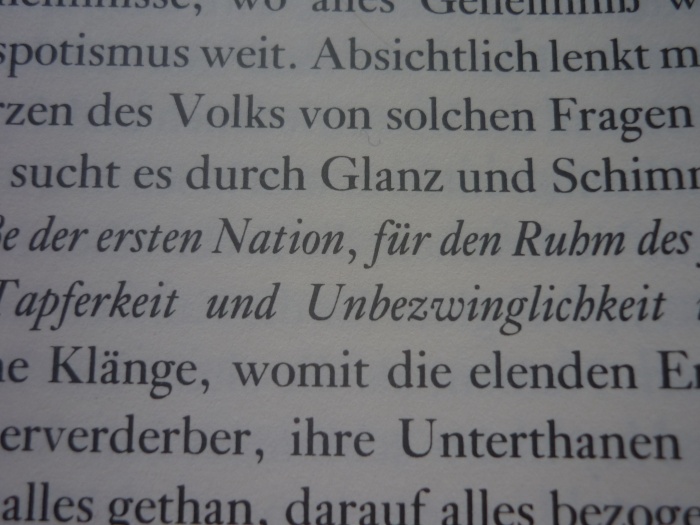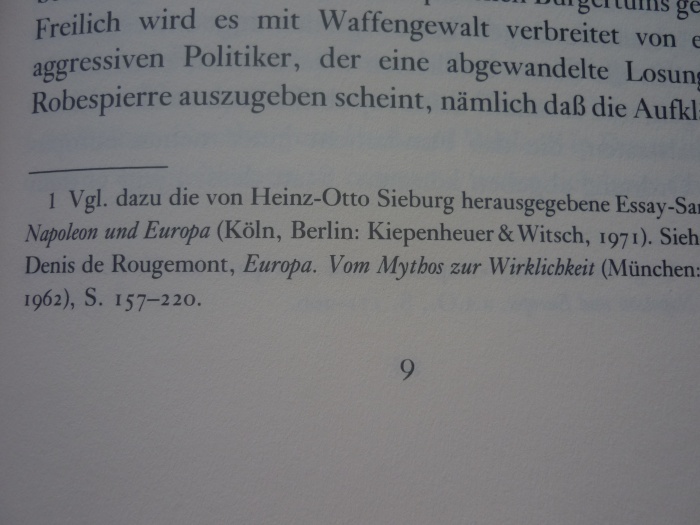
Schriftart insel-Taschenbuch
ich bin zur Zeit auf der Suche nach einer speziellen Schriftart, die im (alten) insel-Taschenbuch Nr. 638 verwendet wurde. Es scheint eine Baskerville zu sein. Folgende Baskerville-Varianten habe ich bereits ausgeschlossen:
ITC New Baskerville Pro
Baskerville Handcut OT
Baskerville FS
Zum Buch selbst können folgende Angaben gemacht werden:
Titel: Europa. Analysen und Visionen der Romantiker.
Hrsg: Paul Michael Lützeler
Satz: Fotosatz Otto Gutfreund, Darmstadt
Verlag: INSEL
Jahr: 1982
Ich habe zwei Bilder zur Identifizierung angehangen. Ich hoffe es findet sich jemand, der bei diesem Fall behilflich sein kann.
PS: Das kursive „J“ hat keinen horizontalen Strich.
Gelöst von Albert-Jan Pool
Eine Baskerville kann es nicht sein, es ist die Linotype Janson. Schau beispielsweise mal genauer auf a und g. Viel zu asymmetrisch um für eine Baskerville durchgehen zu können. Bei Antiqua-Schriften bringt oft einen Vergleich der Kursiven die entscheidende Hinweise.
Die Linotype Janson gibt es bei Linotype nicht mehr. Die Janson wurde in von Stempel für Linotype überarbeitet und ausgebaut als Janson Text, die Schriftfamilie erschien 1986. Dabei wurde anscheinend der Querstrich im J in allen Schnitten wieder eingeführt.
Die Digitalisierungen von Bitstream basieren auf die der Linotype Bibliothek, praktisch so wie sie 1980 bei der Gründung der Firma Bitstream von den ehemaligen Linotype-Mitarbeitern ‘übernommen’ wurde. Aber Bitstream und Linotype gehören inzwischen beide Monotype und auf linotype.com findest Du also jetzt die Linotype Janson die da aber Kis heißt. Die heißt so, weil man später entdeckt hat, dass die Janson eigentlich nicht von Janson ist, aber von Nicolas Kis geschnitten wurde.
Die URW Janson entspricht anscheinend ebenfalls die Linotype Janson, aber so wie es aussieht wurde sie ergänzt um die (wahrscheinlich von Stempel/Linotype stammende) Janson Medium (entspricht Janson Text 75 bold) und die Janson Text (95) black. Inklusive Kursivschnitte. Die Janson Black finde ich zwar in meine 1986er und 1988er Linotype-Kataloge, sie fehlt aber merkwürdigerweise auf linotype.com, sie ist von denen wohl nie als PostScript Schrift herausgebracht worden …
Bei der Schrift läuft es wohl auf einen Kompromiss hinaus. Die URW Janson hat im Kursiv zwar keinen horizontalen Strich im J, aber leider unterstützt sie die Mediävalziffern nur in der URW Janson Regular SC, die es nicht kursiv gibt. Ansonsten passt die Janson Text 55 richtig gut.